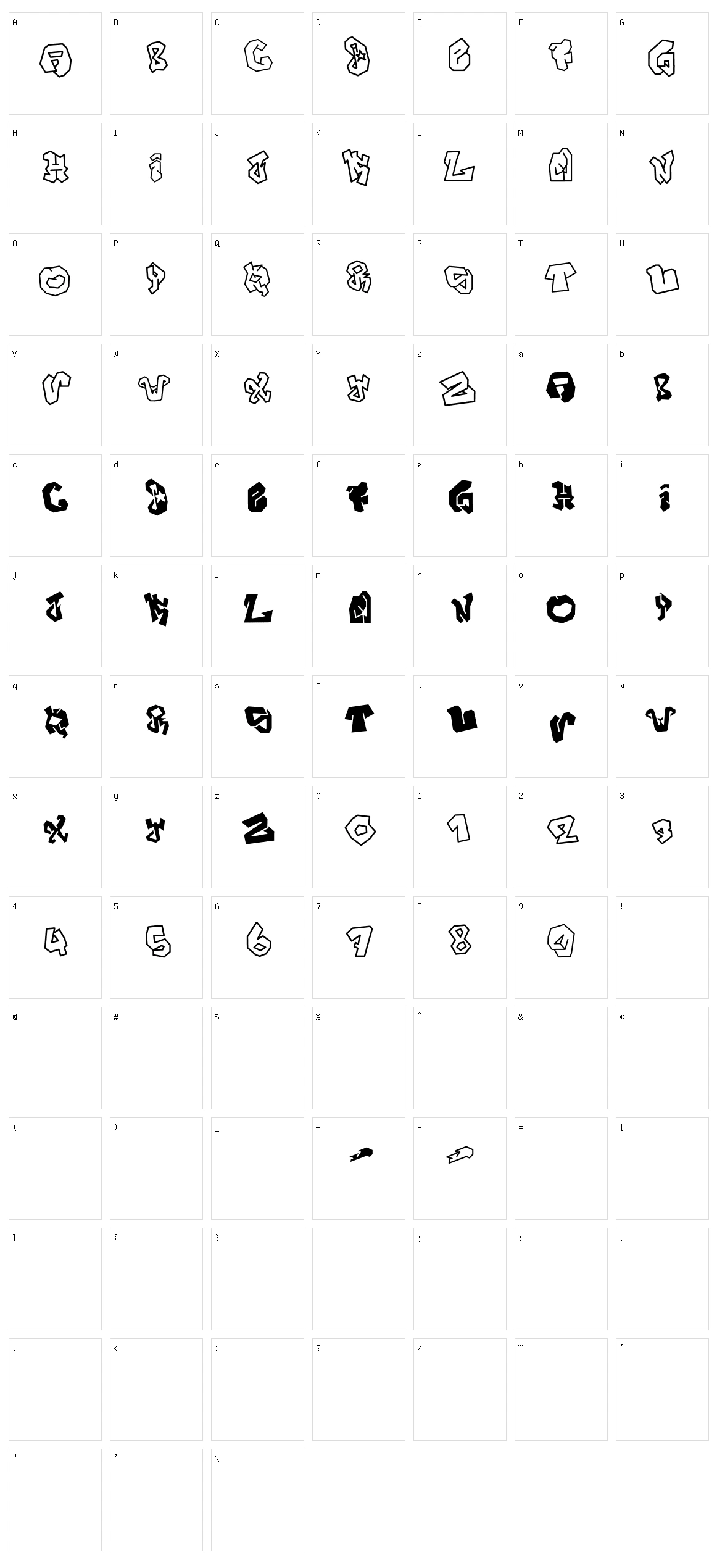
Utilisez les majuscules pour écrire les lettres avec les contours , utilisez les minuscules pour écrire les lettres pleines .....
Combinaison des deux types de lettres :
<<<<<< Exemple pour écrire SIZE :
Tapez SIZE en majuscules .
Ensuite Tapez s en minuscule d'une couleur différente des lettres en majuscules . Superposez le s à l'intérieur du S majuscule . Faites de même pour le I , Z et E . Voila c'est fini !!! :-)